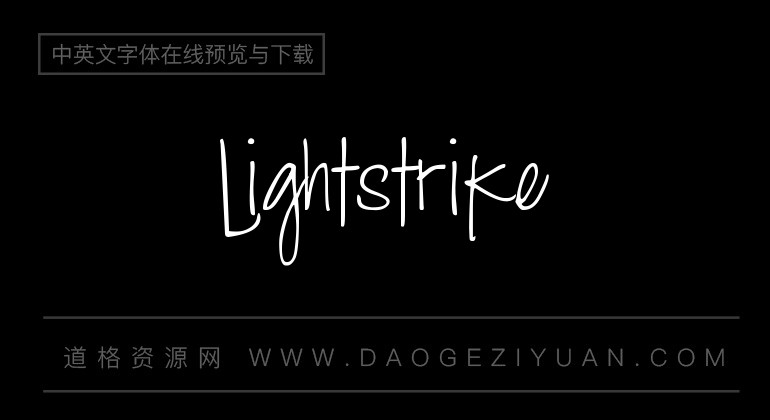
Lightstrike是一种非常现代且独特的字体,它是由设计师Yai Salinas在2016年创造的。 这种字体与许多其他字体不同,因为它具有非常锐利的角度和角度,这使得它看起来非常动态和现代。 Lightstrike的字母非常简洁,而且字母之间的间距非常紧密,这使得它非常适合于时尚、科技和其他现代领域的设计。 此外,它的线条非常细,因此它可以轻松地用于各种大小的设计。 总体而言,Lightstrike是一种非常具有创意和独特性的字体,它可以为您的设计提供一种非常现代的外观和感觉。内容介绍
Lightstrike是一款非常不错的手写艺术字体,具有很好的视觉感,适合于文化类的宣传设计、商业类品牌的广告和产品包装设计以及个性化文字排版等较多场景。